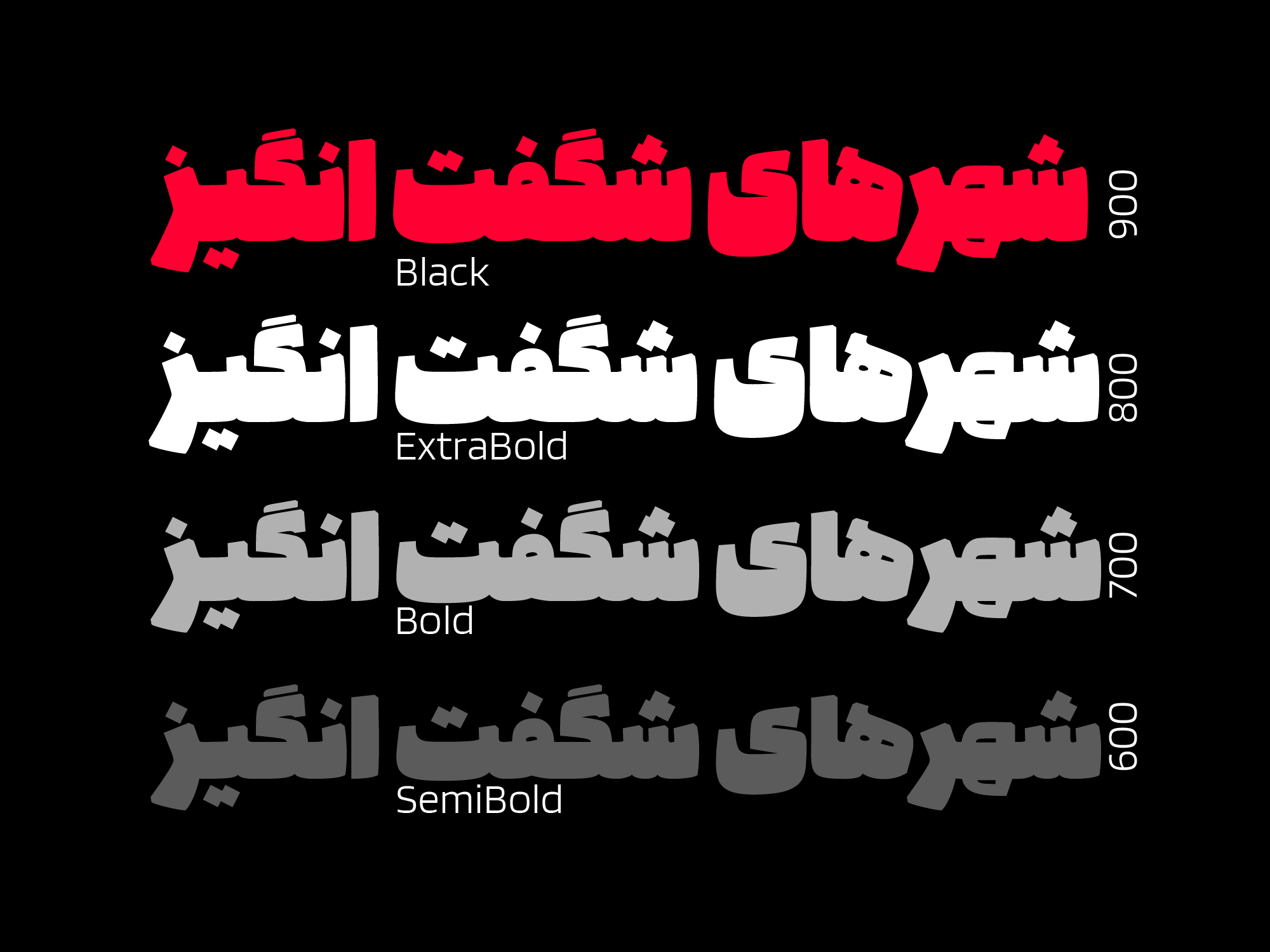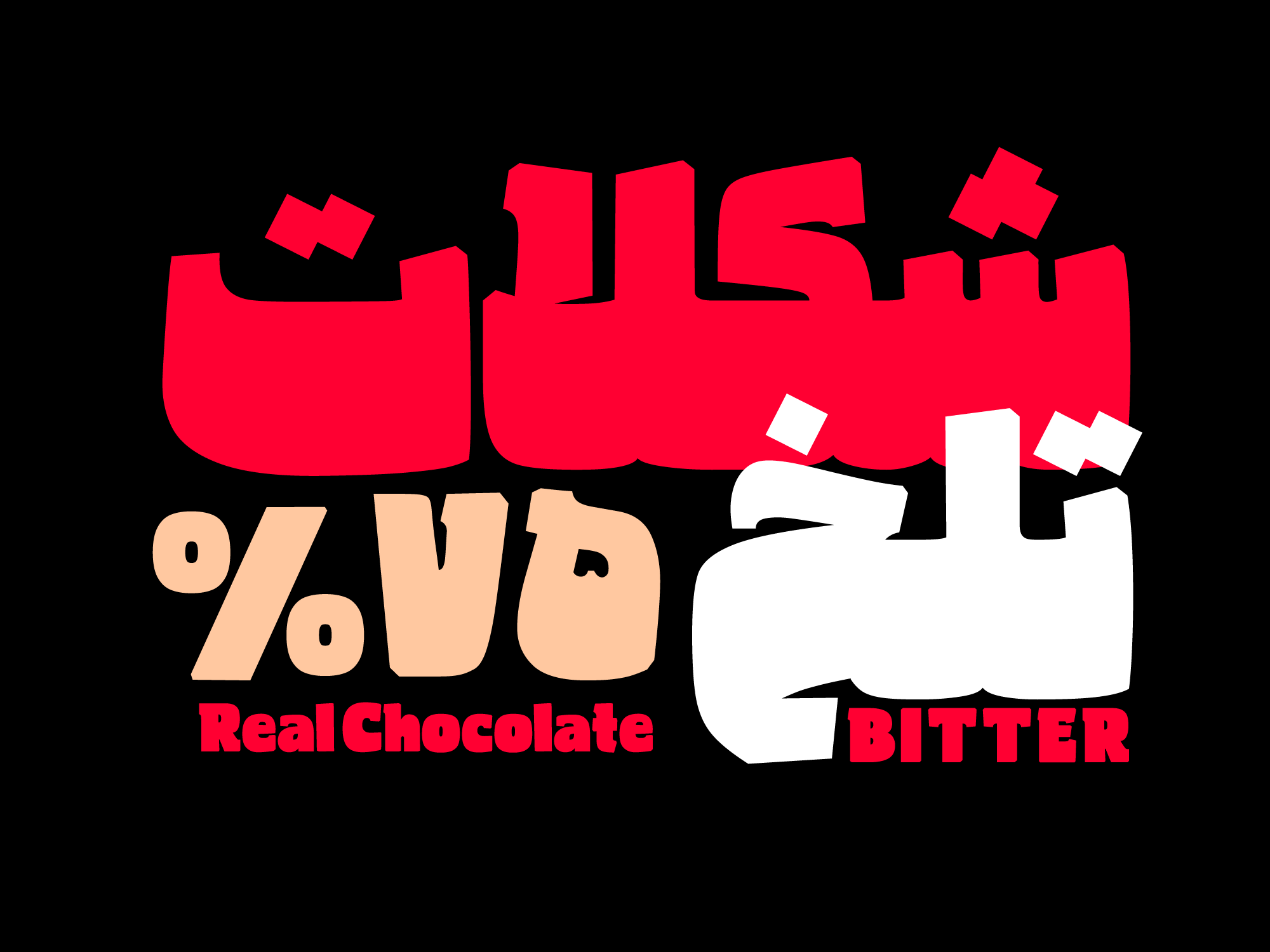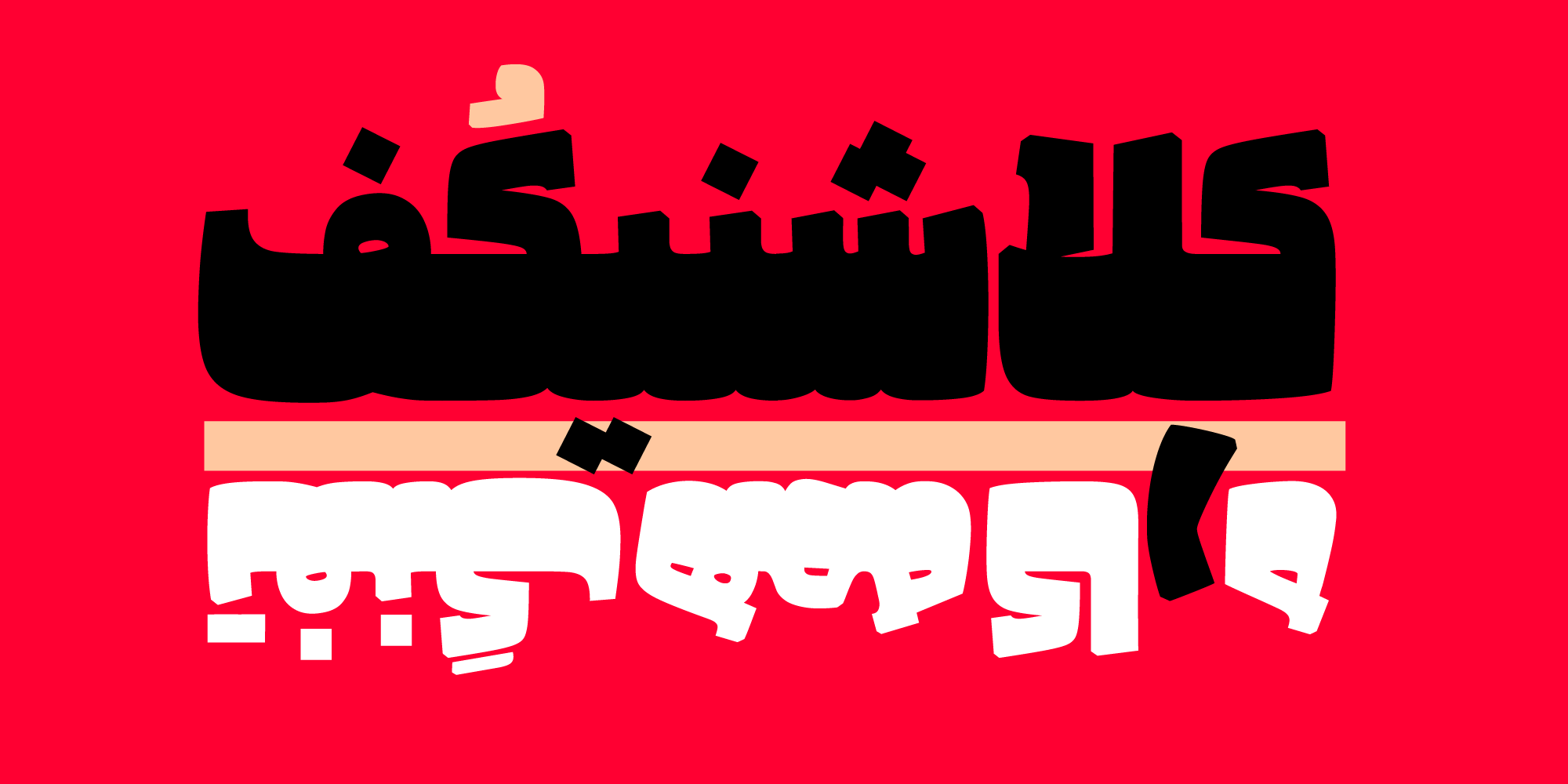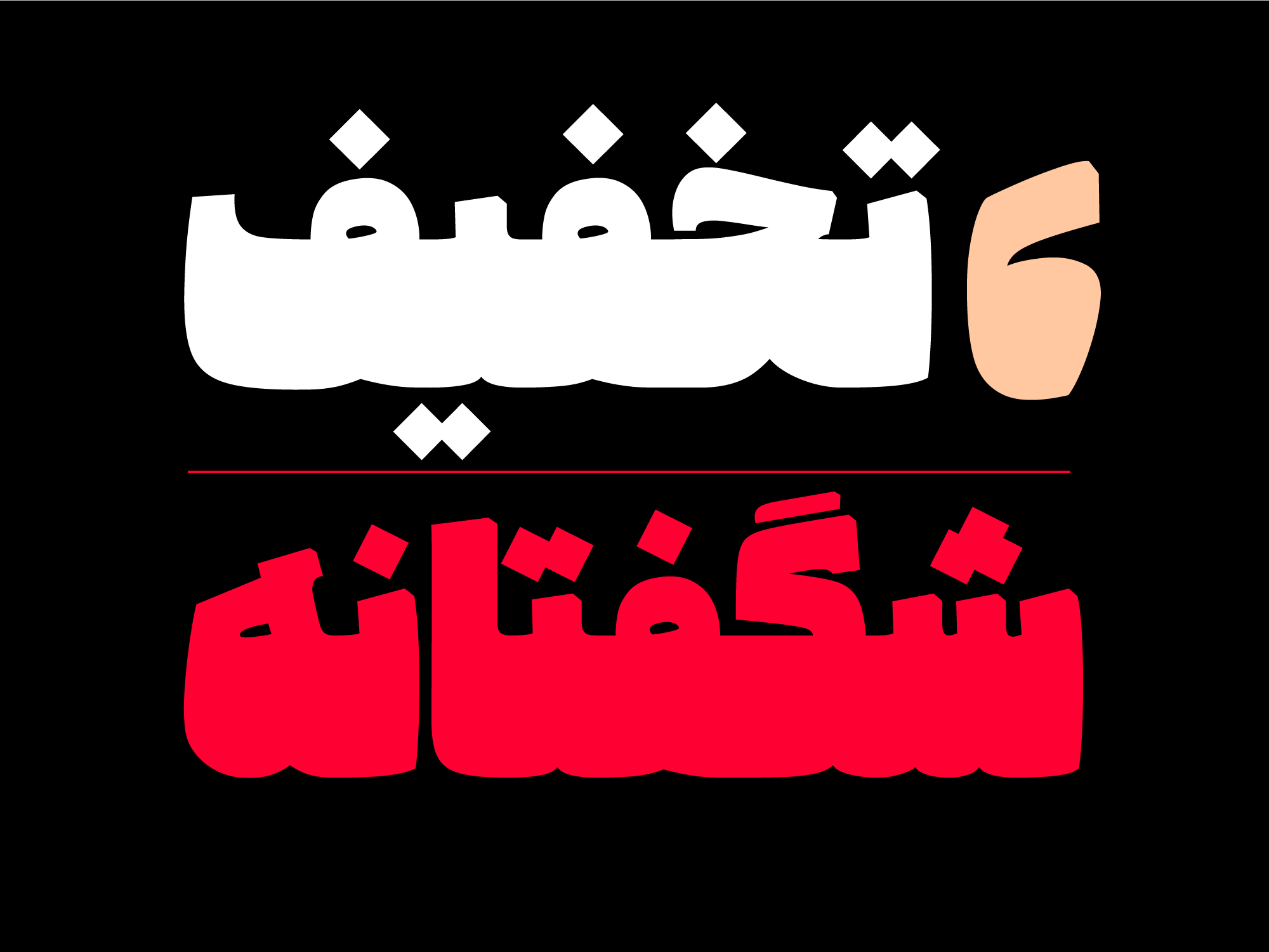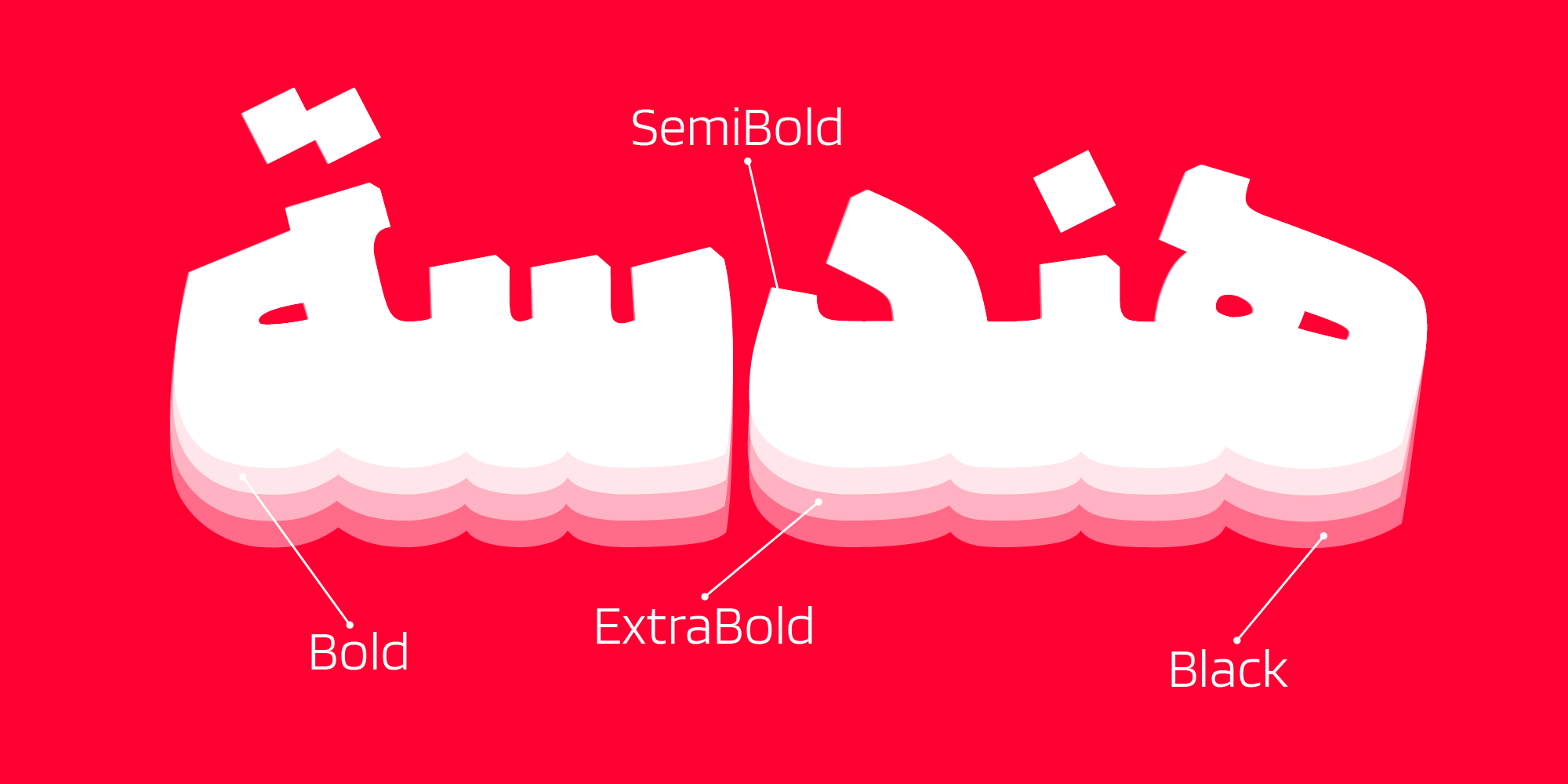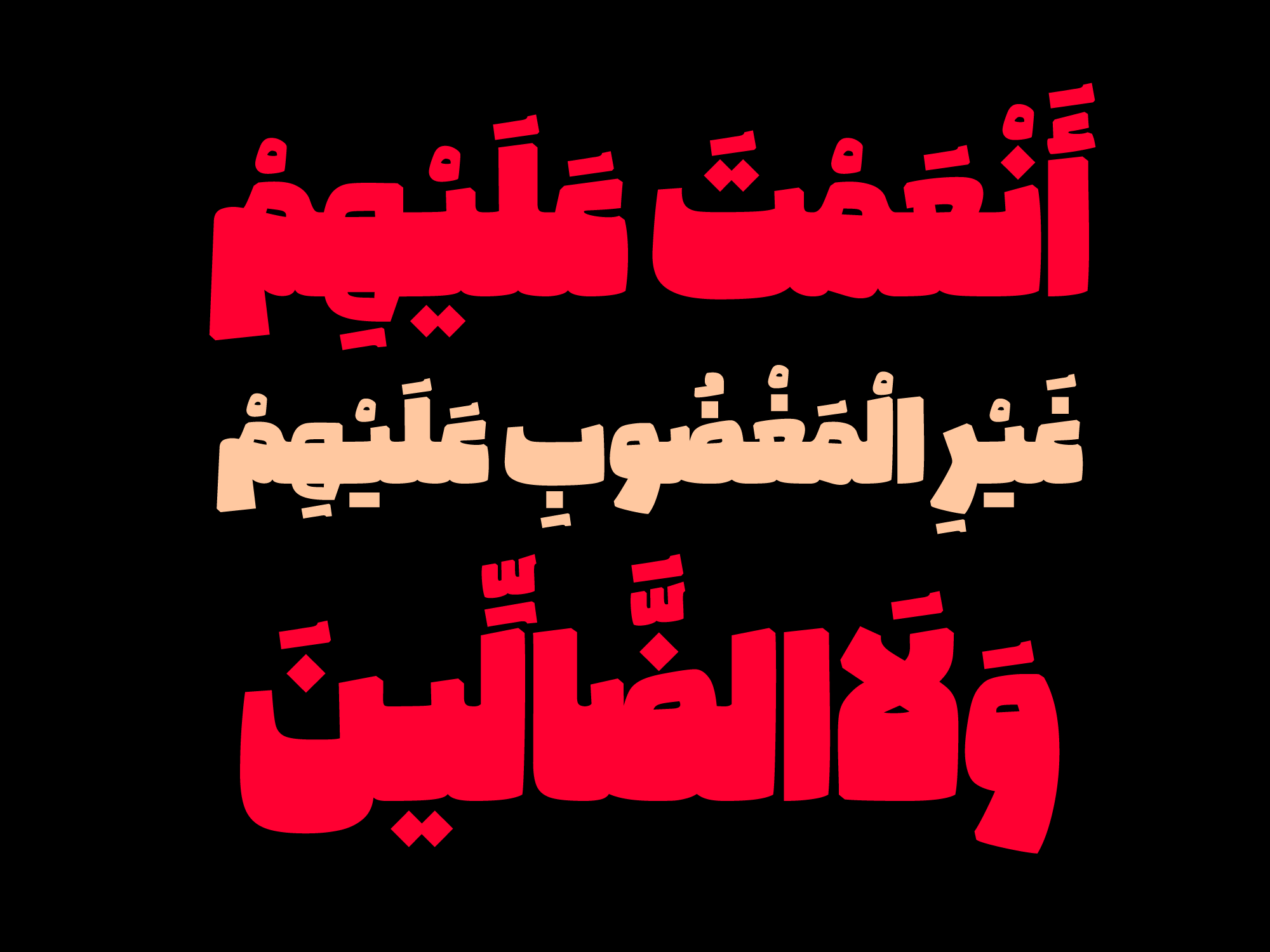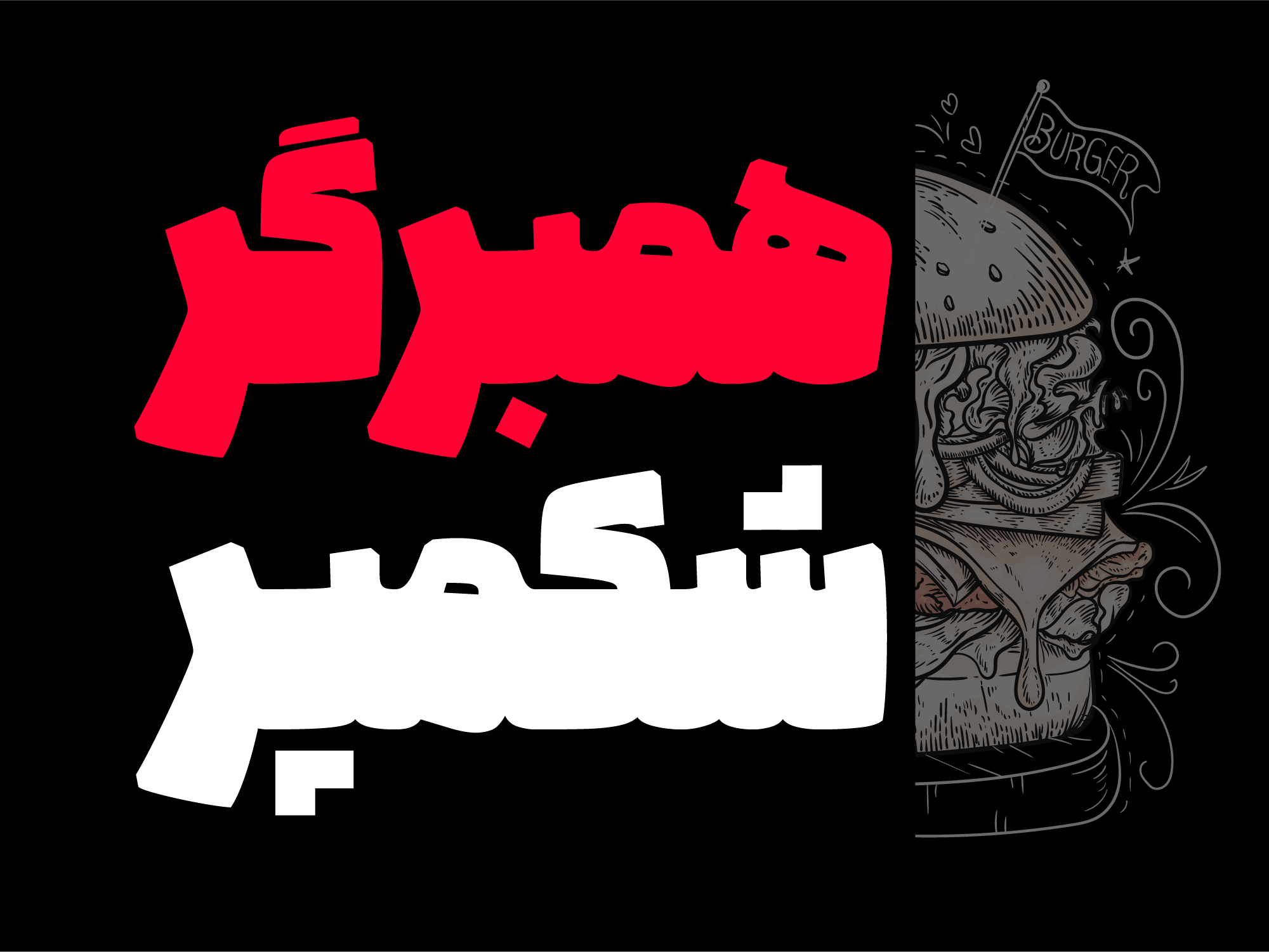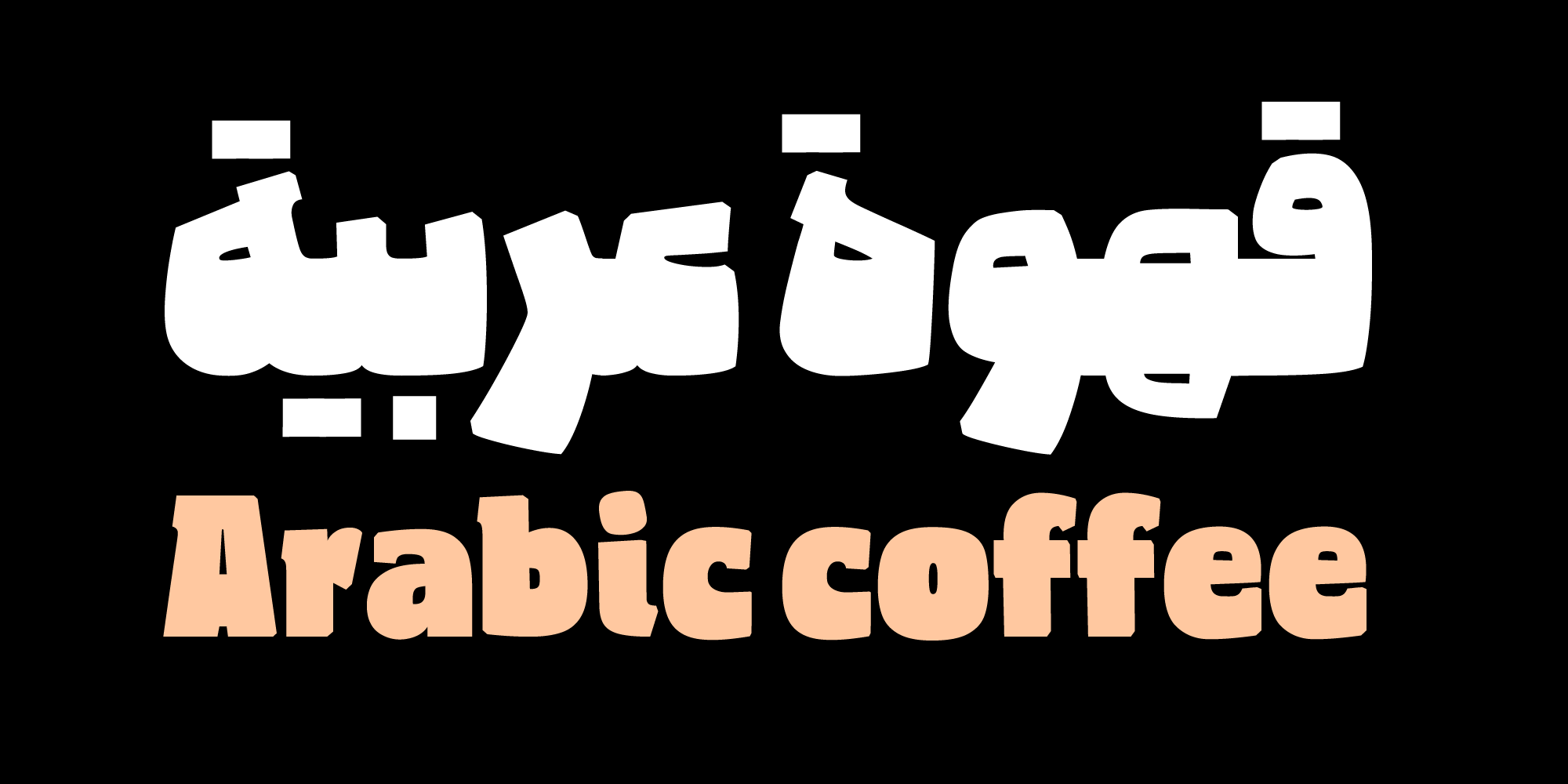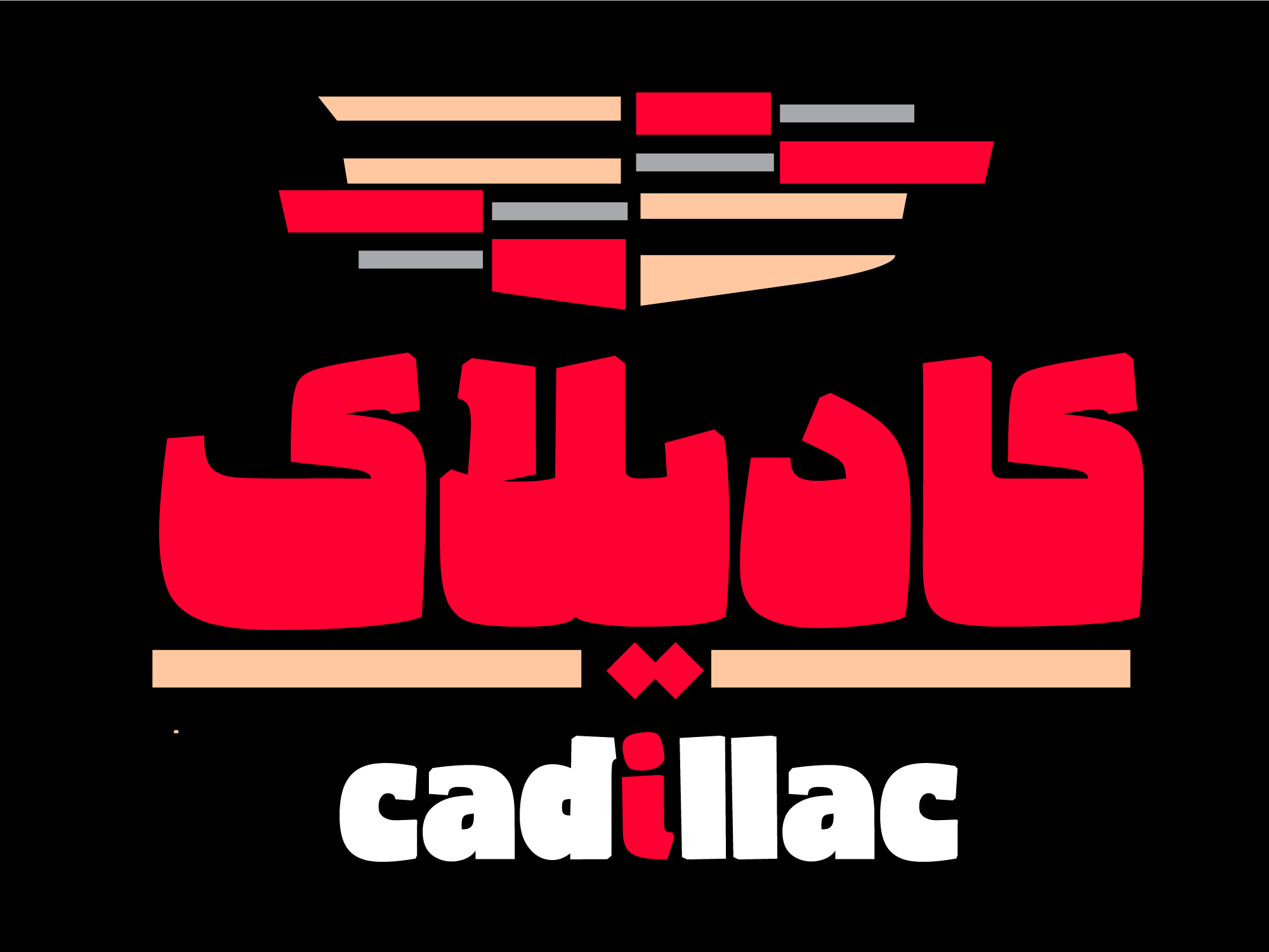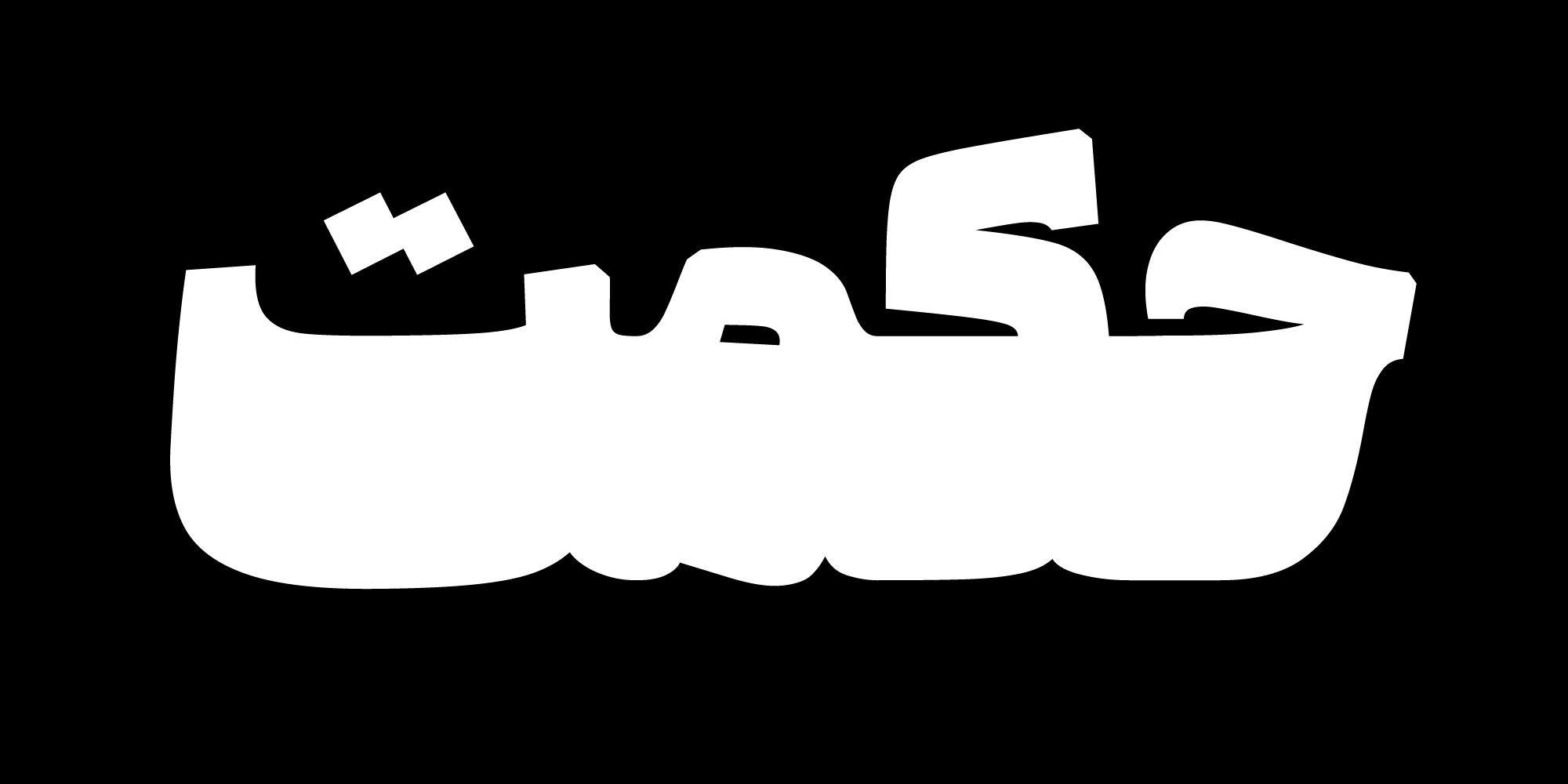
تنوع وزنها در فونت سنگین
یک خانواده کوچک چهار عضوی چاق و چله با پنج حالت نقطه گذاری برای هر کدام که در مجموع بیست استایل متفاوت ارائه میکند.
ترکیبها و حروف جایگزین
فونت سنگین ترکیبات (Ligature) و حروف جایگزینی (Alternative) متعددی دارد.
امکان تغییر شکل نقطهها
در فونت سنگین پنج حالت نقطه گذاری وجود دارد.